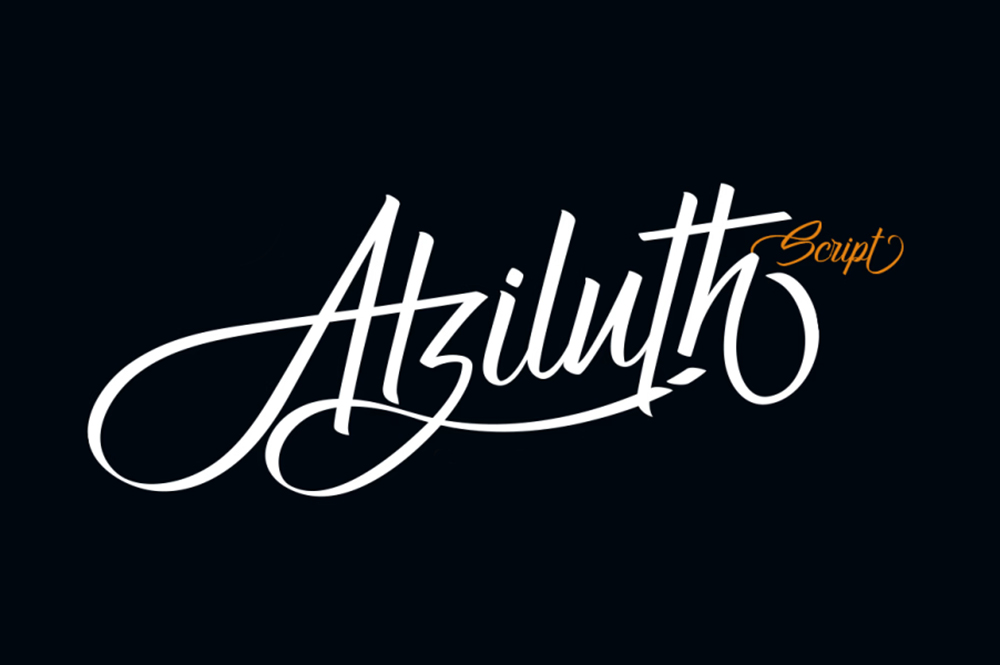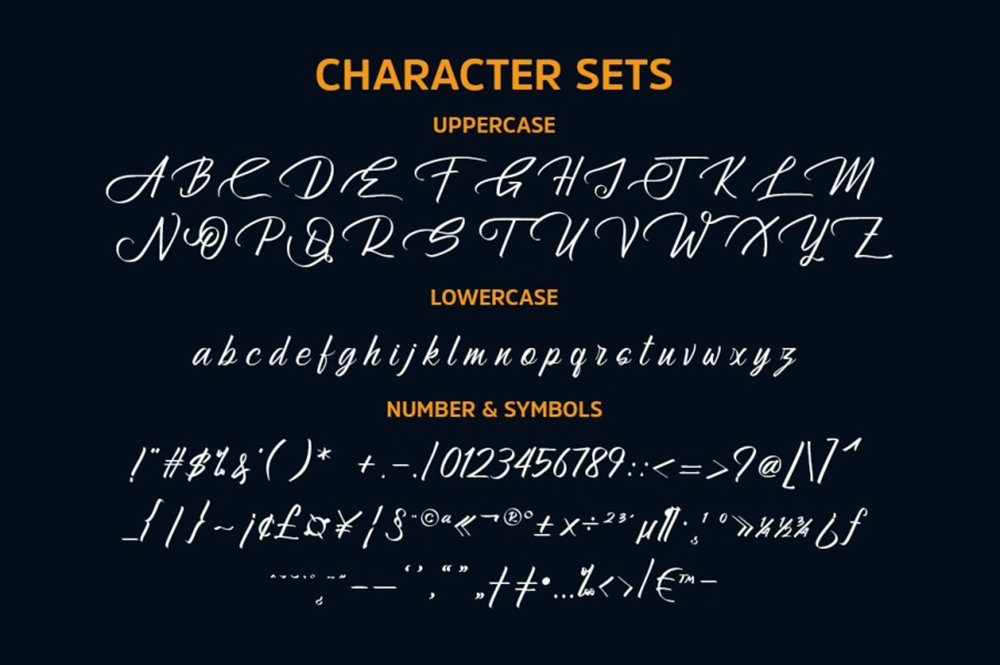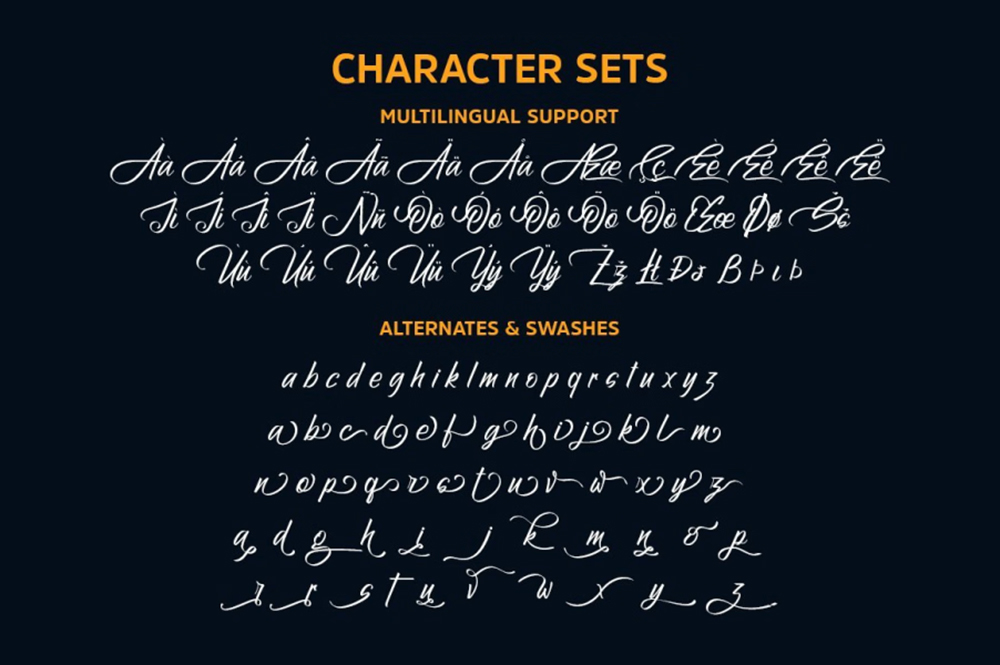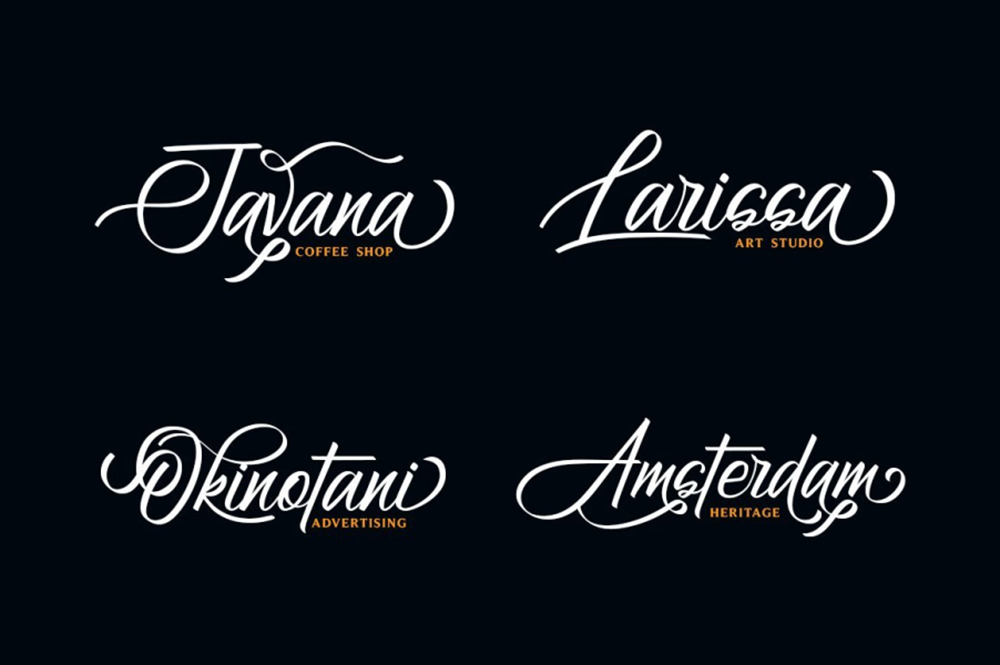
فونت پرمیوم و انگلیسی Atziluth Font یک فونت نوشتاری زیبا بر اساس سبک خوشنویسی است. این یک فونت نمایشی قابل دسترس و انعطافپذیر است که دارای تعداد زیادی جایگزین و لیگاتور برای اهداف برندسازی یا لوگوتایپ میباشد. این فونت برای اهداف مختلفی مانند امضا، برندسازی، نقل قول، عنوان کتاب/جلد، پوستر، طراحی لباس، بستهبندی محصول، برچسب، رویدادهای ویژه یا هر چیزی که نیاز به سلیقه و ظرافت دارد، عالی است.
مزایای استفاده از فونت لاتین Atziluth چیست؟